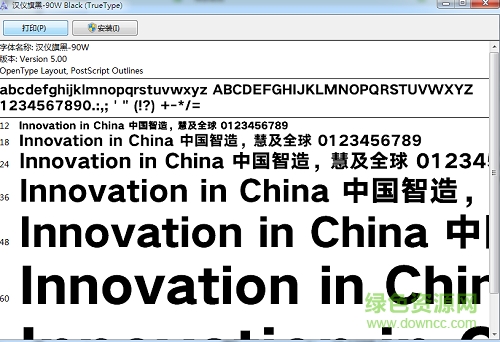
hyqihei izw字體又稱漢儀旗黑90w,是一款擁有潮流時尚風格的字體,整體效果比較正規(guī),引領潮流,十分耐看,有需要用到這款字體的朋友歡迎來綠色資源網(wǎng)下載!
hyqihei izw是一款用于藝術設計方面的字體,文藝黑體筆畫正真大方,富含濃烈的文學藝術,整體效果比較正規(guī),適用于各大廣告標題設計!